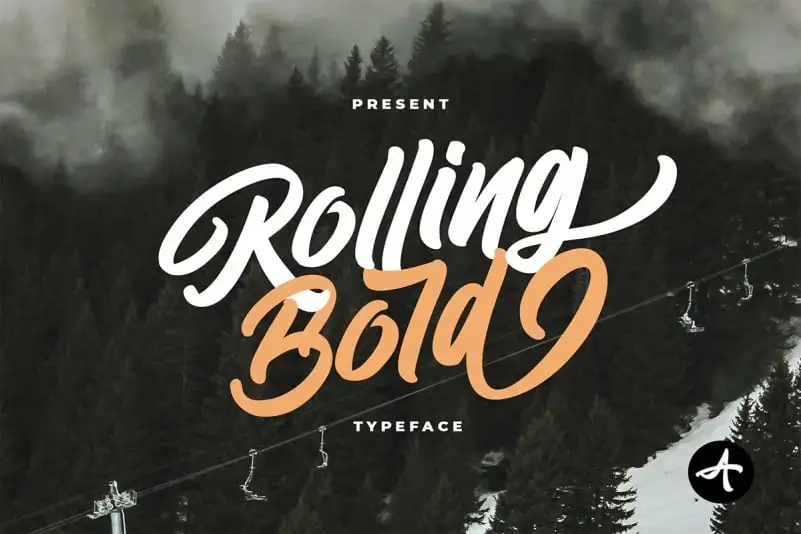
Rolling Bold Script Font – Download Grátis
A Rolling Bold Script Font é uma elegante tipografia script bold que traz um tom autêntico e casual ao seu design. Inspirada nos estilos vintage moderno e retro, ela combina elementos do estilo tradicional americano antigo. Esta fonte de script moderna foi projetada para incrementar a beleza dos seus designs. É muito fácil de usar e pode economizar tempo em sua criação. Além disso, Rolling Bold também oferece muitas funcionalidades opentype como ligaduras e alternativas que permitem uma ampla gama de personalização. Esta fonte é ideal para ser usada em logotipos, cartazes, embalagens, produtos, mídia social e cartões de agradecimento.